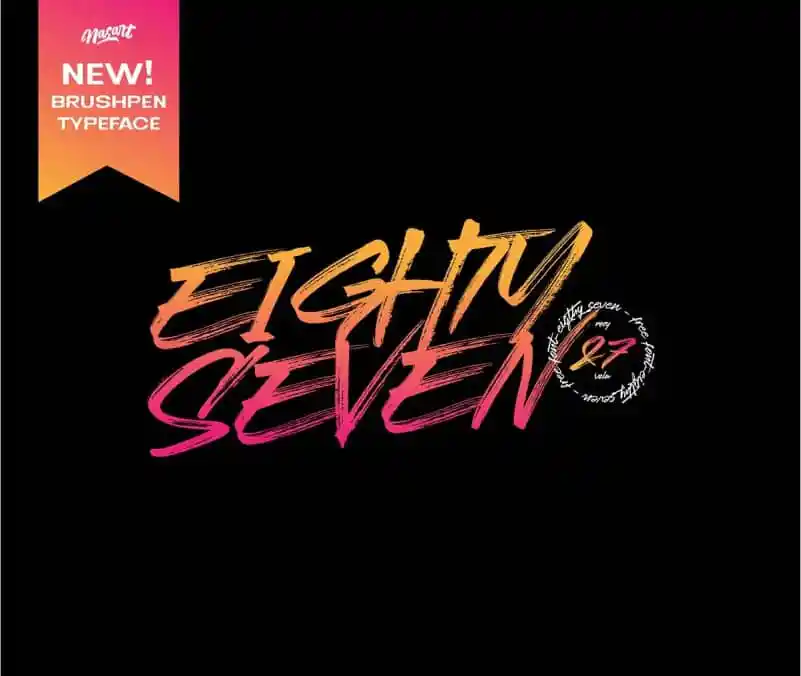
Eighty Seven Brush Font – Download Grátis
O Eighty Seven Brush Font é uma fonte de estilo script criada usando uma lousa seca. Este tipo especial foi desenvolvido pela Hamilton, e possui uma sensação casual que se assemelha a escritas a mão de alguém apressado. Ideal para design de moda, logotipos, catálogos, capas de livros ou revistas, este font está equipado para dar vida aos teus trabalhos de arte. Tem um toque autêntico e cuidadosamente realizado, perfeito para assinaturas, embalagens, rótulos, identidades visuais, cabeçalhos de websites, etiquetas, materiais de publicidade ou qualquer design que queiras dar um toque pessoal. Este font é sua chave para criar um design artesanal único e moderno.